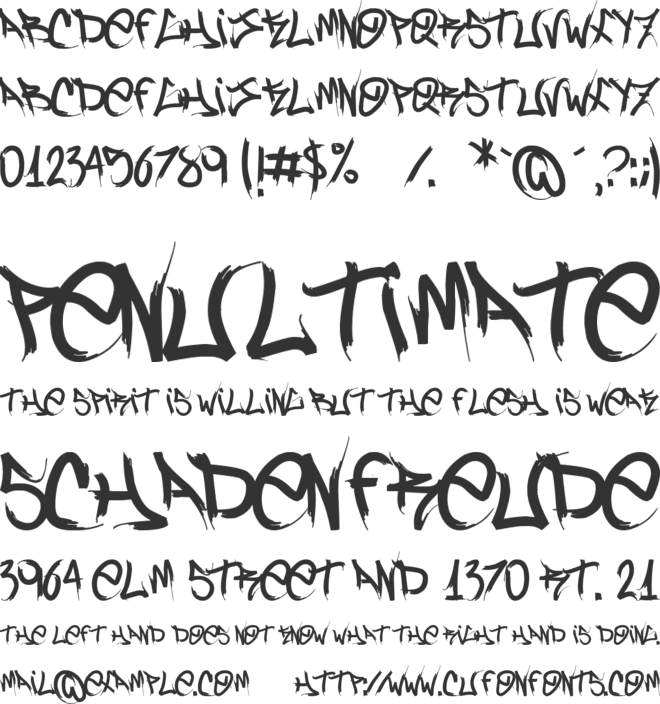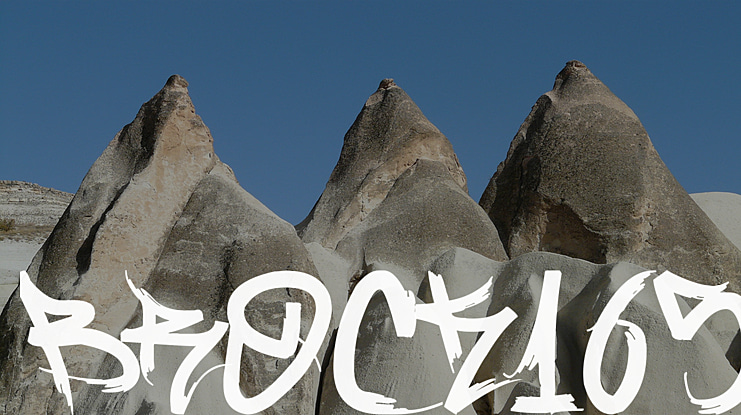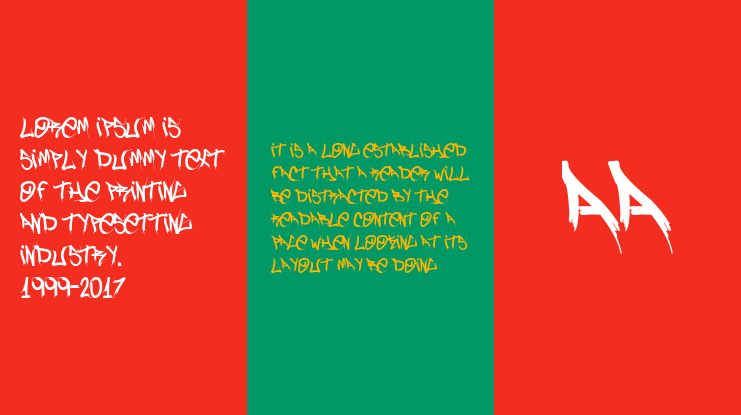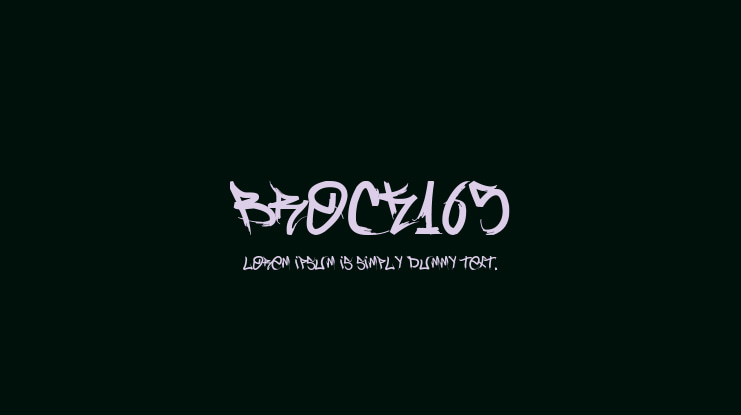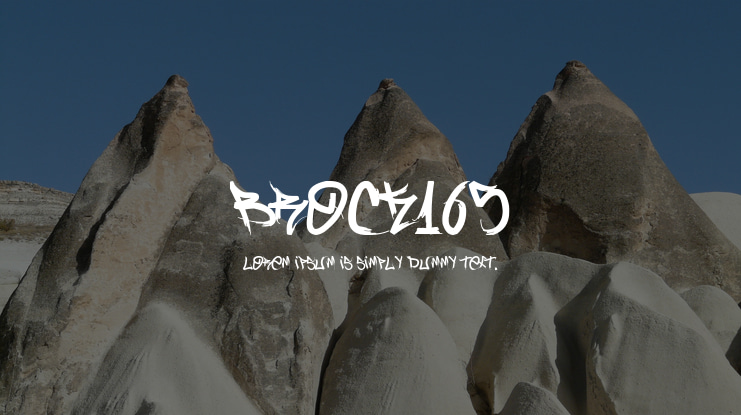
Brock165 Font
A tipografia Brock165 Regular foi criada com base nos graffitis urbanos da cidade de Manaus. Essa família possui apenas elementos em caixa alta, numerais e alguns principais caracteres. Quando utilizá-la me envie o link do seu trabalho para que possa prestigiar sua criatividade! Obrigado!